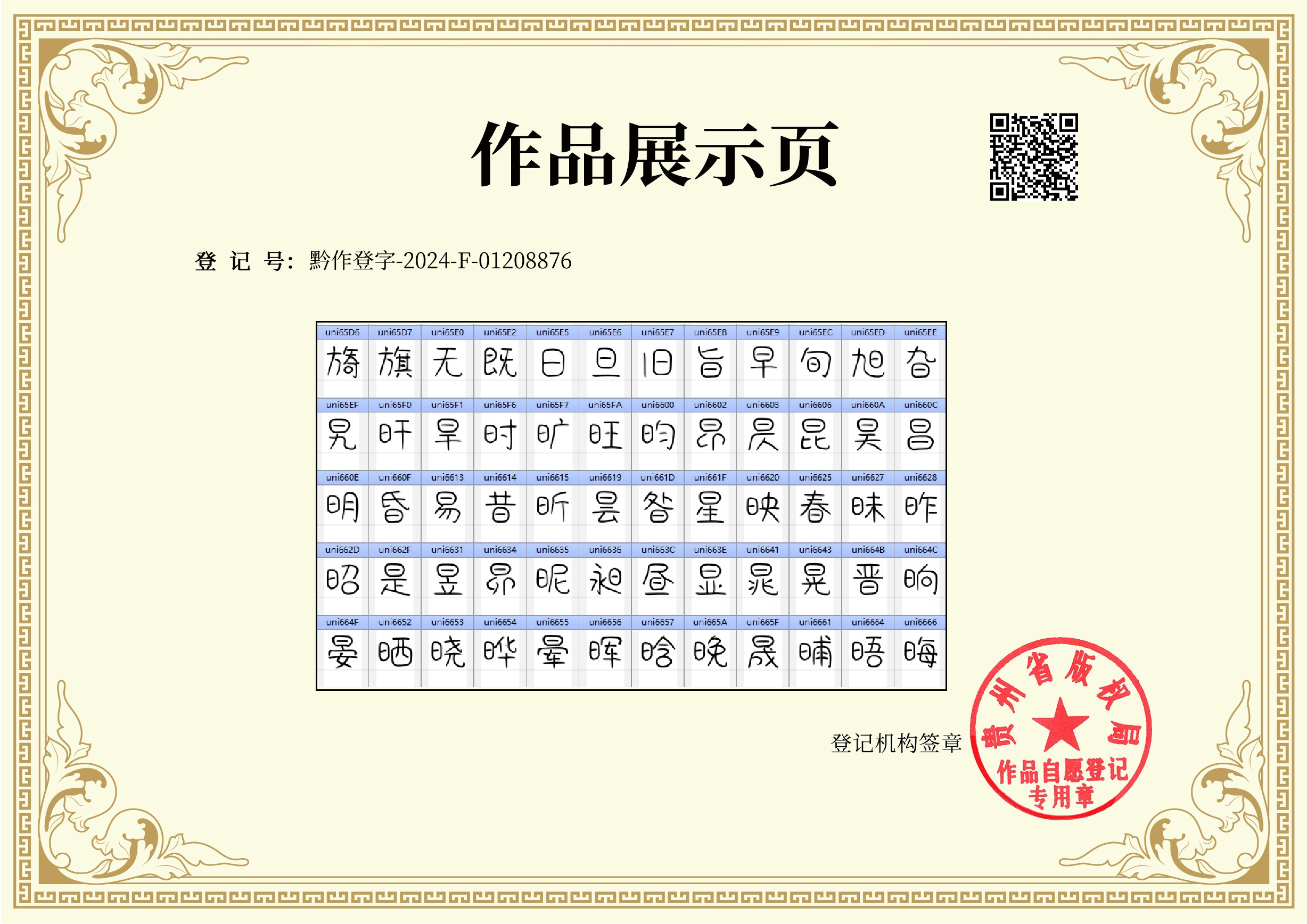
自由理想体
自由理想体是网友李力发布的一款免费商用字体,首发于其博客胡搞虾搞。自由理想体目前已涵盖GB2312标准的6763字,您可以放心下载使用。
以下是作者发布时的原文引用:
礼品卉 自由理想体
既然是自由体嘛,那就要洒脱一些,没有那么多的规矩;本该横的地方,它横得没那么直,本该竖的地方,它又竖得没那么利索;有点像你在家里躺在沙发上看电视剧的姿势,“葛优躺”见过吗?嗯,就那样;凡是框框的地方,都用圈圈代替,比如《品》字,画三个圈圈祝福你,直到永远!